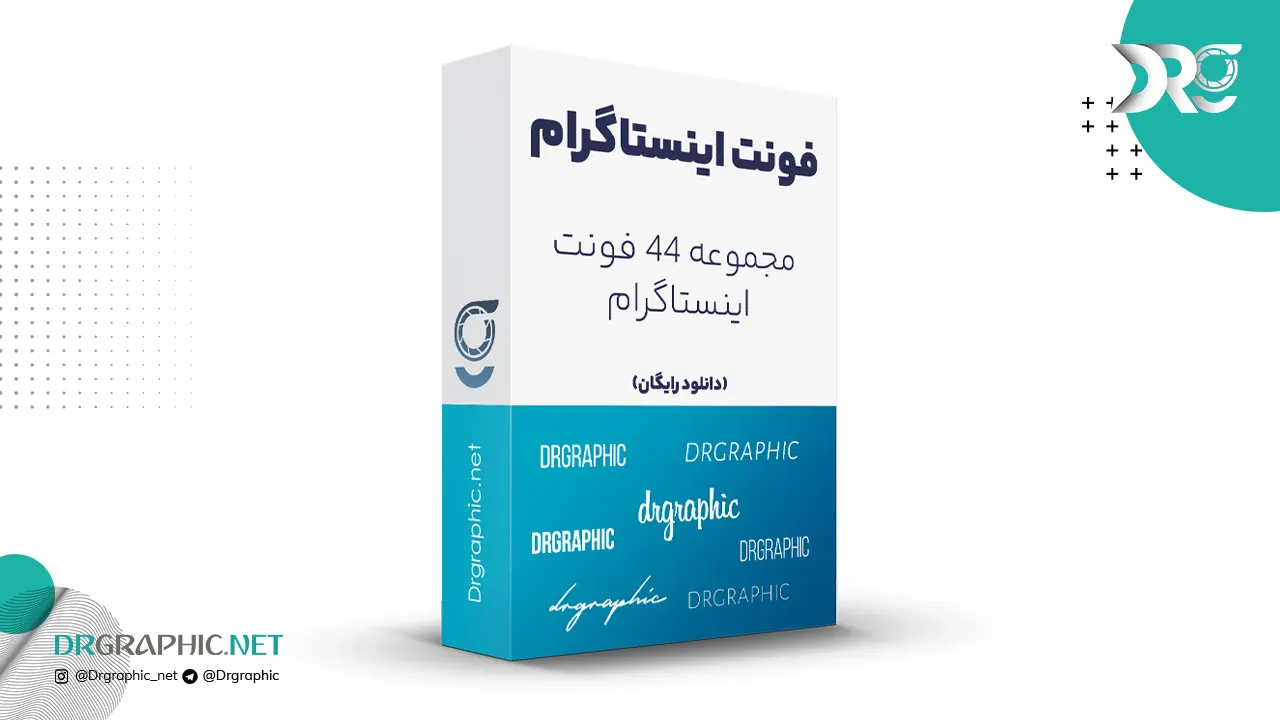
دانلود مجموعه فونت رسمی اینستاگرام instagram
با دانلود مجموعه فونت اینستاگرام از دکتر گرافیک، می توانید برای جلد کتاب، جلد موسیقی، کتاب کودک، پوستر، تبلیغات، محتوای رسانه های اجتماعی و موارد دیگر از آن استفاده کنید.
نمونه نوشته با این فونت:
دانلود مجموعه فونت رسمی اینستاگرام instagram
مجموعه فونت اینستاگرام instagram